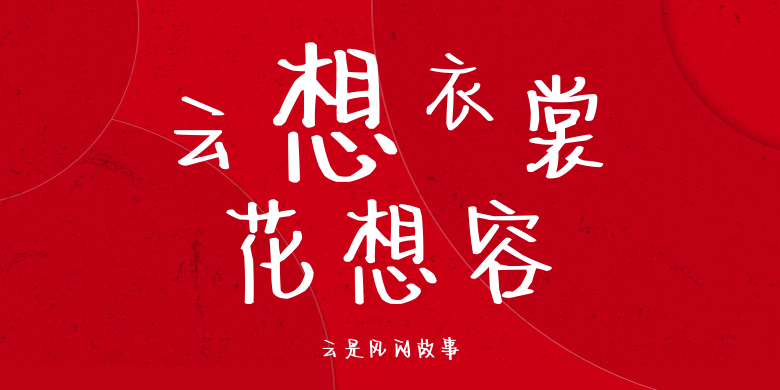
云是风的故事
云是风的故事,这款字体结构工整、笔画清晰,兼顾美观与易读性,适用于标题、正文、海报、包装、LOGO 等多种场景。字形优雅稳定,风格百搭耐看,适配日常排版与创意设计,让文字呈现更舒适、更具质感。云是风的故事一笔一画,皆是细节,以均衡的比例、流畅的线条打造舒适视觉体验,字形端正大气,风格简约现代。无论是商业设计、品牌宣传还是日常排版,都能轻松驾驭,让文字更有格调与力量。云是风的故事字体下载。